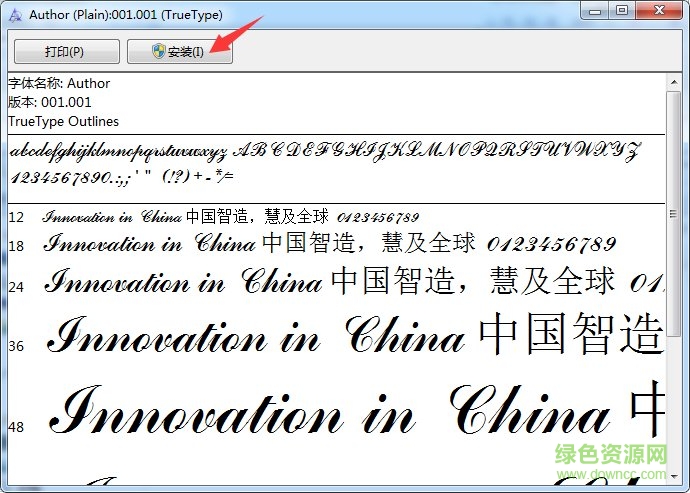
author字體是一款免費(fèi)的英文字體。輸出的英文字體非常飄逸,可以用來設(shè)計(jì)時(shí)尚雜志、海報(bào)宣傳冊等。除了可以輸出英文內(nèi)容外,小編試了下輸出簡體中文或者數(shù)字的話效果不是很明顯!喜歡的用戶快來下載吧。
Author字體是一款適用于創(chuàng)意設(shè)計(jì)方面的字體,主要用在印刷設(shè)計(jì)、廣告設(shè)計(jì)等行業(yè)。下載后讓你能夠盡情使用其中的任何字體進(jìn)行文字編輯帶來獨(dú)特的文字顯示風(fēng)格!